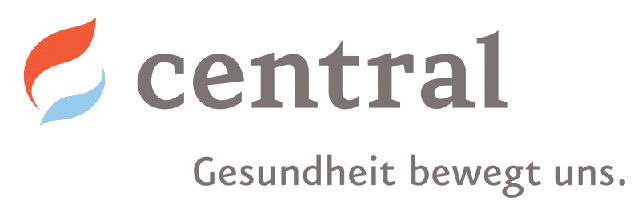
Central-Versicherung-Schriftarten bei neuem Logo?
weiß einer von euch vielleicht, welche beiden Font die Central Versicherung für ihr neues Logo verwendet.
Ich dachte erst, die Serifenschrift wäre die Charter und die Zweite die Gill Sans. Sie sind es aber nicht.
Wenn keiner eine Lösung weiß, vielleicht gibt es ja etwas sehr ähnliches. das würde auch schon helfen.